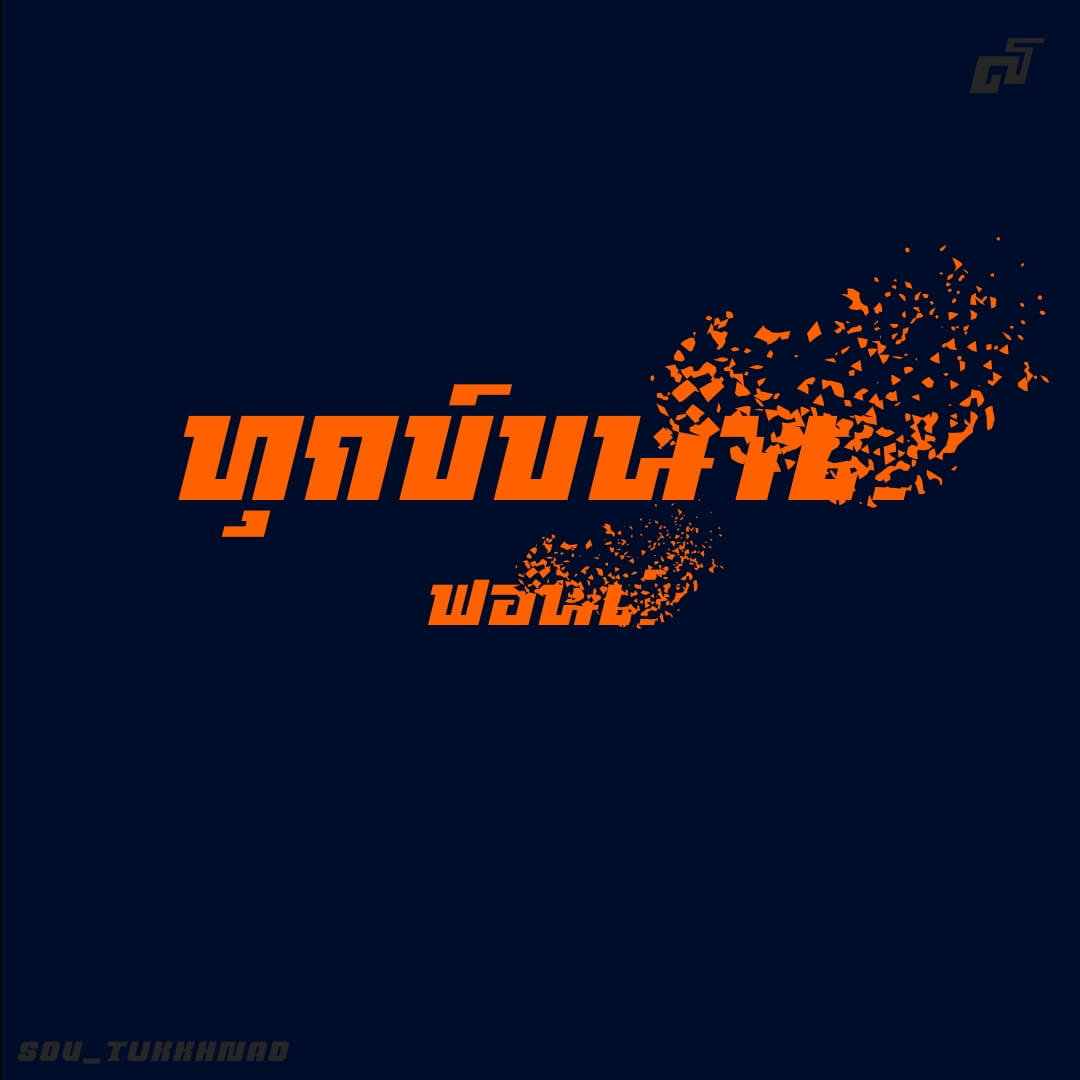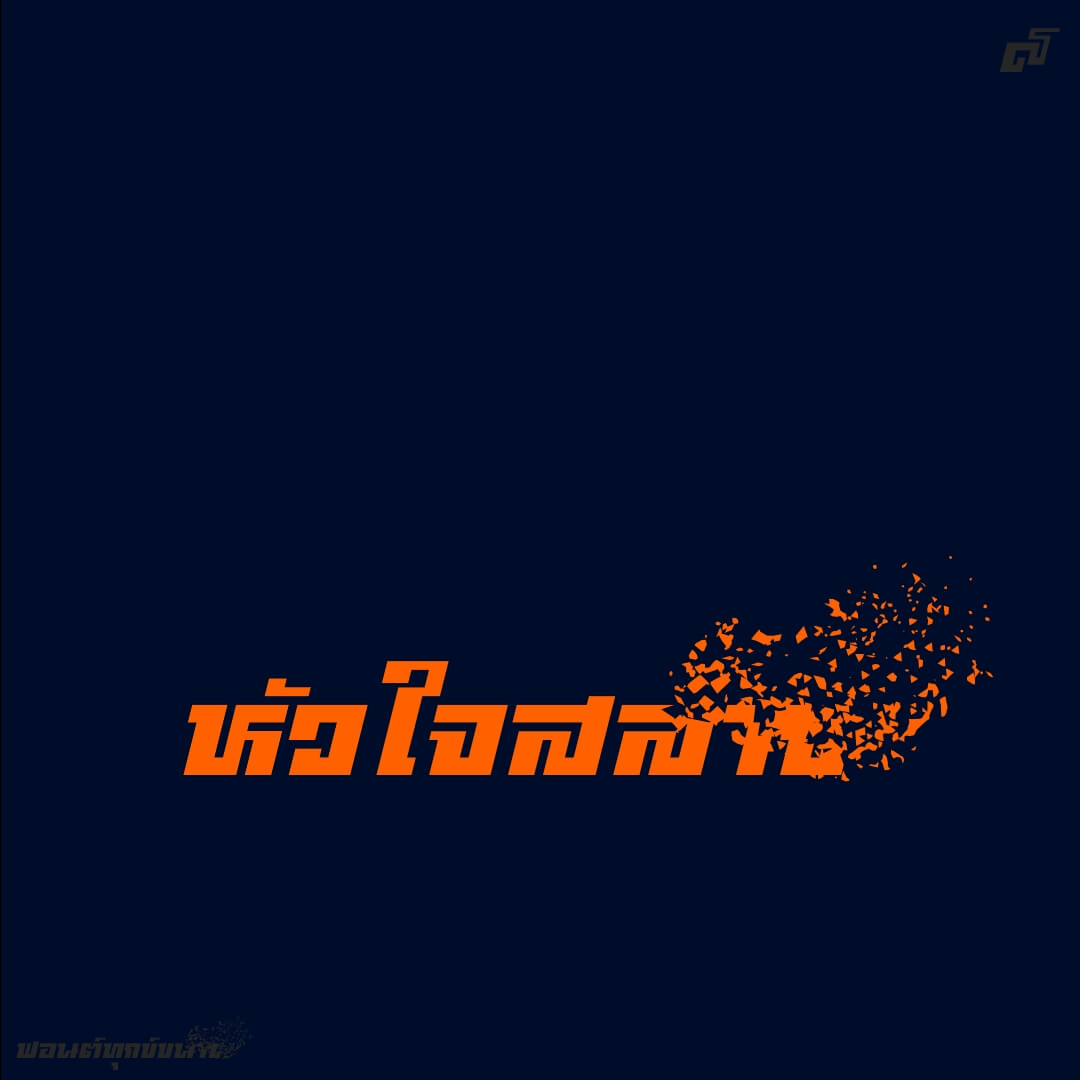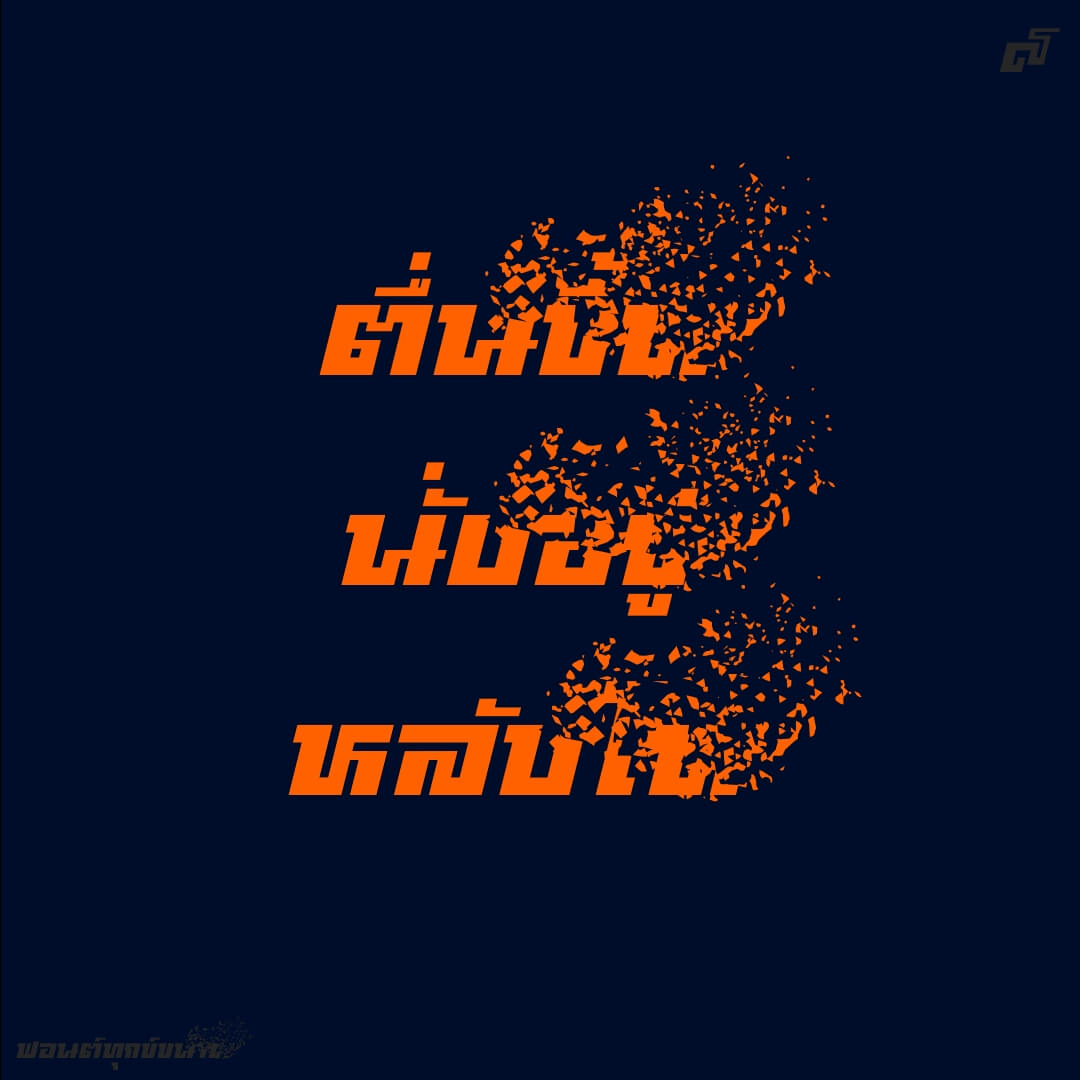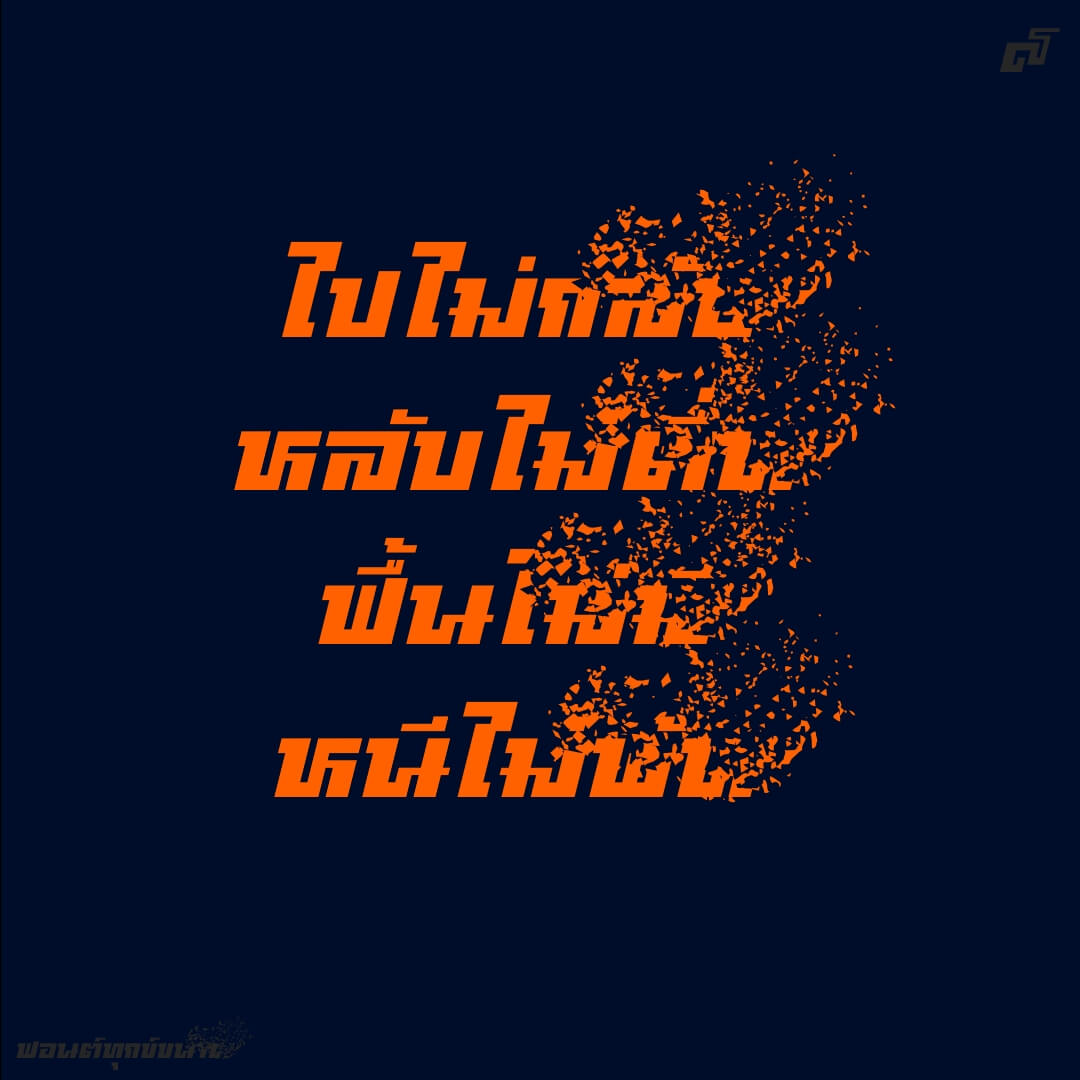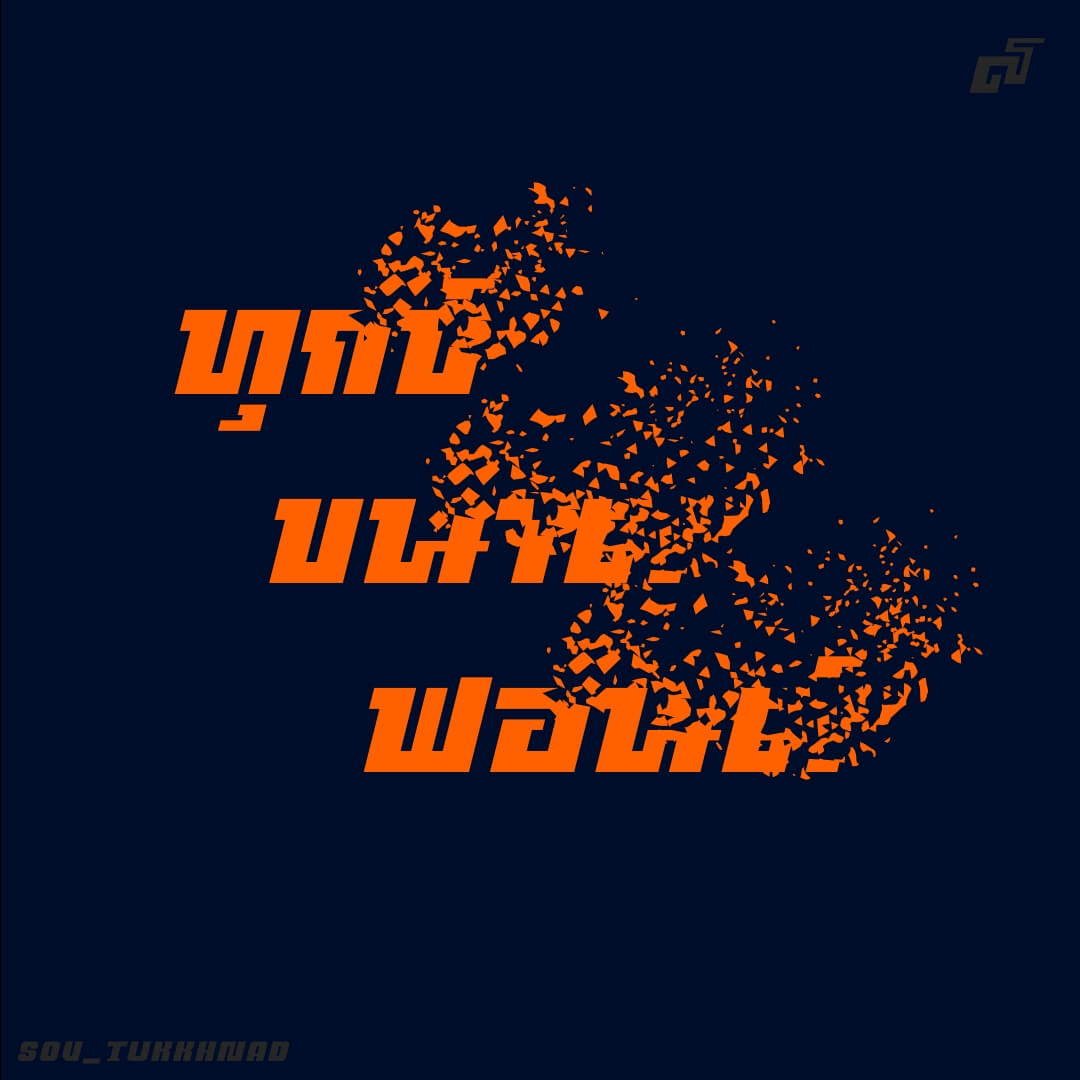
ทุกข์ขนาด (SOV_TukKhnad)
ฟอนต์ทุกข์ขนาด – จาก คงขนาด หลายขนาด ไปต่อที่ ทุกขนาด (VF สินะ) พ้องเสียงเป็น ทุกข์ขนาด ทุกข์มาก ใจสลาย ก็เลยกลายเป็นฟอนต์นี้… ใช้เฉพาะทาง เหมาะแค่บางคำ บางประโยคนะ!